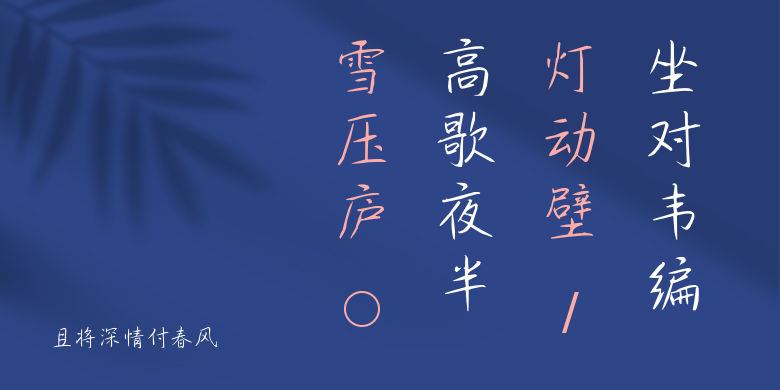
且将深情付春风
且将深情付春风,这款字体结构工整、笔画清晰,兼顾美观与易读性,适用于标题、正文、海报、包装、LOGO 等多种场景。字形优雅稳定,风格百搭耐看,适配日常排版与创意设计,让文字呈现更舒适、更具质感。且将深情付春风一笔一画,皆是细节,以均衡的比例、流畅的线条打造舒适视觉体验,字形端正大气,风格简约现代。无论是商业设计、品牌宣传还是日常排版,都能轻松驾驭,让文字更有格调与力量。且将深情付春风字体下载。